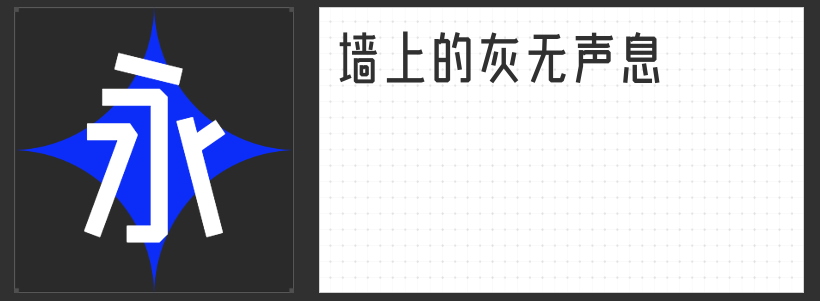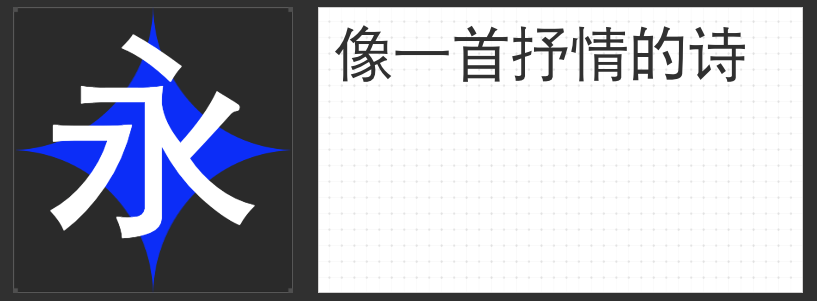
四款专业级正文设计字体推荐:平衡美感与功能的排版利器
在信息爆炸的时代,优秀的正文设计需兼顾视觉美感与阅读舒适度。本文精选四款兼具专业性与适用性的字体,它们以独特的结构语言与视觉节奏,为各类设计场景提供稳定而富有表现力的文本支撑。
一、高手庆科竞速体 常规
这款以“竞速”为灵感的字体,通过瘦长工整的轮廓构建出理性秩序感。其核心设计突破在于:中宫紧凑却不显局促,布白均匀如精密齿轮咬合;直线主导的笔画系统实现视觉等粗,去钩处理与平切收笔赋予文字现代工业的冷峻美感。四个字重形成的渐变体系,既能以细体呈现轻盈呼吸感,又可通过粗体强化视觉层级,在科技类、运动类文本排版中展现出独特的张力美学。
二、励字魔方黑简
作为强调视觉冲击力的代表,励字魔方黑简以方正字形构建出稳定的视觉基座。方头方尾的笔形设计形成强烈的黑白对比,横竖笔画粗细的戏剧性差异(竖粗横细)在保证远距离可读性的同时,创造出动态的视觉韵律。这种去装饰化的极简风格,使其在信息图表、导视系统等需要快速传达的场景中,成为建立视觉秩序的高效工具。
三、励字玉树临风简
取法传统碑刻的瘦长结构,励字玉树临风简通过修长端正的字形传递出文人气质。其设计精髓在于“拙中见巧”——笔画的适度弧度与均匀留白形成含蓄的韵律感,平直收笔与微妙粗细变化在克制中展现书写温度。这种既保留传统美学基因又符合现代阅读习惯的设计,使其成为文化类、艺术类文本排版的理想选择。
四、励字中等线简
作为经典无衬线字体的进化版,中等线简以绝对理性的设计语言诠释“功能优先”原则。全等粗的笔画与方头方尾结构形成高度统一的视觉矩阵,横平竖直的布局确保极端字号下的可读性。这种去个性化的设计特征,使其在法律文件、数据报告等需要绝对严谨的场景中,成为建立专业信任感的无声语言。
这四款字体通过差异化的设计策略,共同构建起正文排版的多元美学体系。无论是追求机械美学的科技感,还是钟情东方韵味的含蓄表达,或是需要绝对理性的信息传达,它们都能以专业级的表现力,为设计注入持久而稳定的视觉能量。